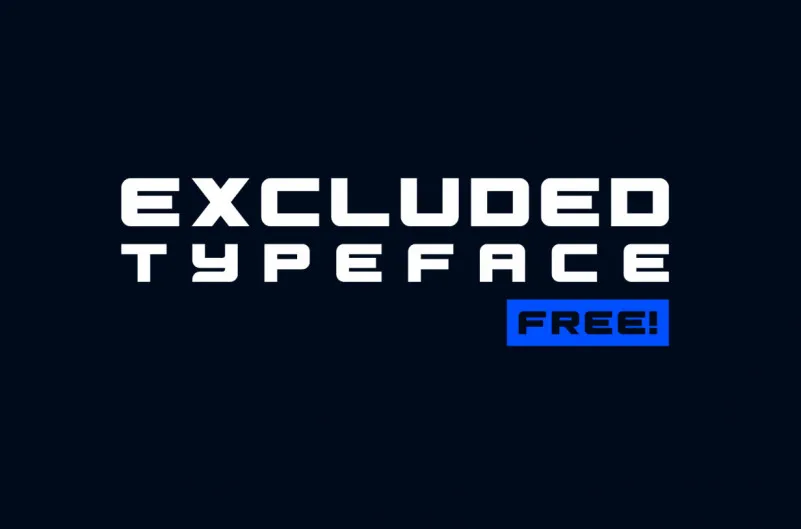
Esta nova fonte ‘Excluded Typeface’, criada pelo designer Hamilton, traz uma visão futurista e minimalista ao design de caracteres diretos. Com sua rigidez angular e contraste alto, a Excluded Display Type é ideal para dar um toque artesanal a qualquer projeto. Esta fonte é perfeitamente adaptável para aplicações em diversas áreas, como marcação, logotipos, revistas ou filmes. Além disso, o uso de diferentes pesos da fonte oferece uma ampla gama de possibilidades criativas, enquanto os formatos sólidos e linhas delineadas conferem um ar moderno a qualquer projeto. A Excluded Typeface é perfeita para quem busca incorporar elementos contemporâneos em seus projetos visuais sem comprometer o aspecto direto dos caracteres. Este recurso gráfico não apenas reflete a qualidade estética da fonte, mas também seu valor funcional para designers que buscam uma combinação única de rigidez e sofisticação em suas criações digitais.